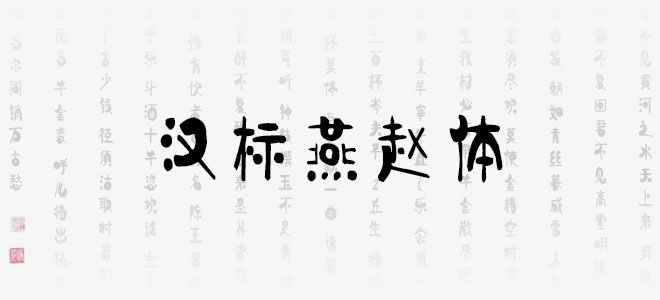
漢標(biāo)燕趙體是漢標(biāo)字庫推出的一款藝術(shù)字體,涉及字中帶口元素的基本書寫成了圓圈,豎為細(xì),既遒勁有力又不失文雅風(fēng)韻的特色字體。作者自幼學(xué)習(xí)書法,后臨學(xué)各傳統(tǒng)名派書法,至成年歷經(jīng)生活滄桑。集數(shù)年所學(xué)及人生感悟融于此款字中,每一筆每一劃都能體現(xiàn)出沉著穩(wěn)重、滄海桑田、剛?cè)岵?jì)又不失傳統(tǒng)書法之特色。歡迎喜歡漢標(biāo)燕趙體的朋友前來下載使用。
漢標(biāo)燕趙體